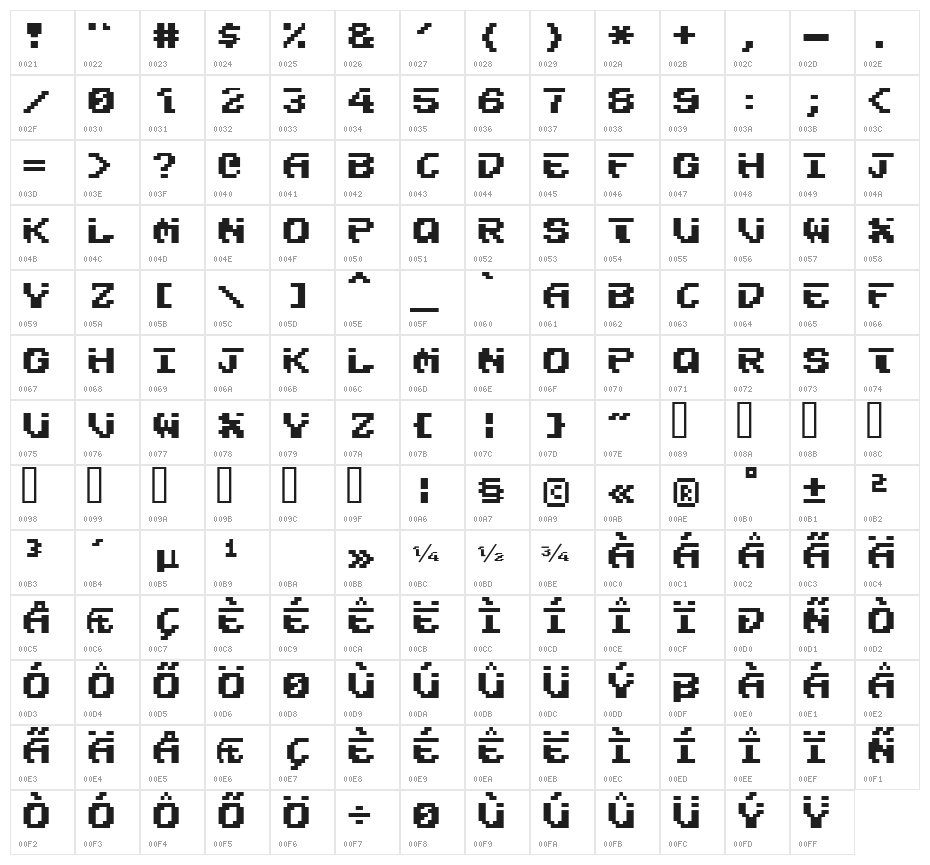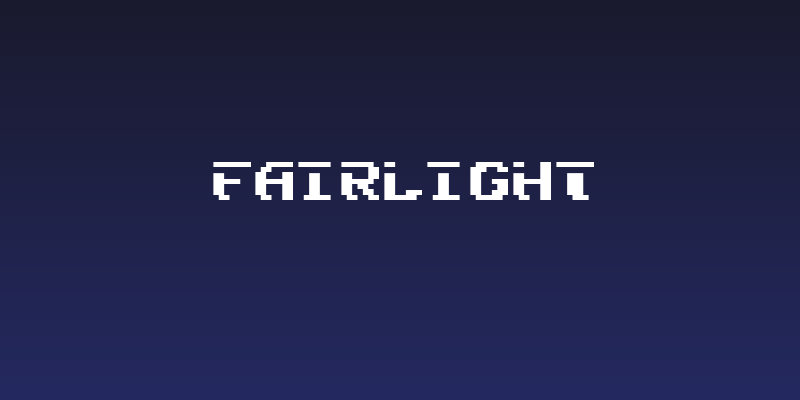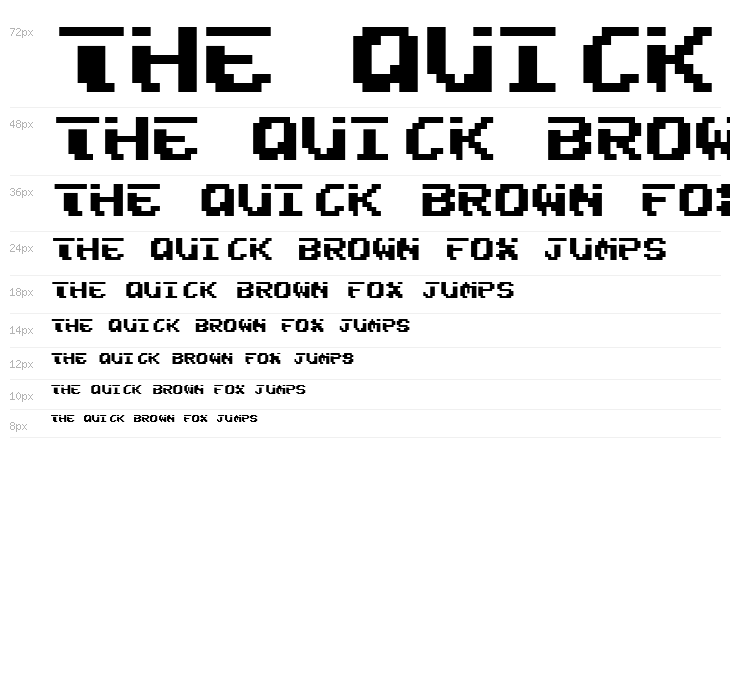
Fairlight Font
| Gesamtstil | Retro, Digital |
| Vorgeschlagene Projekte | Ideal for retro video games, tech-themed posters, digital art projects, and any design requiring a nostalgic digital feel. |